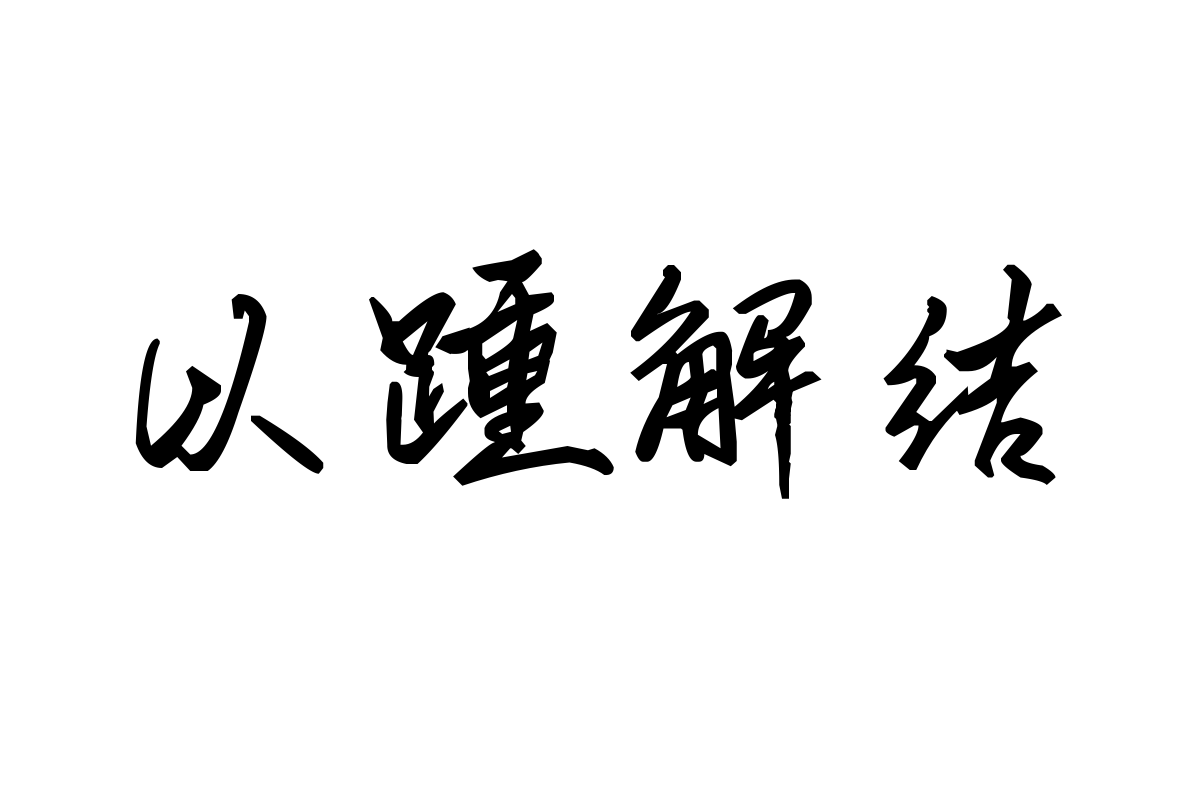
米开一纸相思体是一种手写体,起源于中国宋朝时期。这种字体的特点是笔画流畅,结构紧凑,给人一种优雅、古朴的感觉。它的字形类似于汉字的草书,但又不同于传统的草书,更注重笔画之间的连接和平衡。
米开一纸相思体的笔画粗细不一,有的笔画较细,有的笔画较粗,但整体上呈现出一种和谐的美感。这种字体在书法艺术中具有很高的价值,被广泛用于书法创作和欣赏。
米开一纸相思体